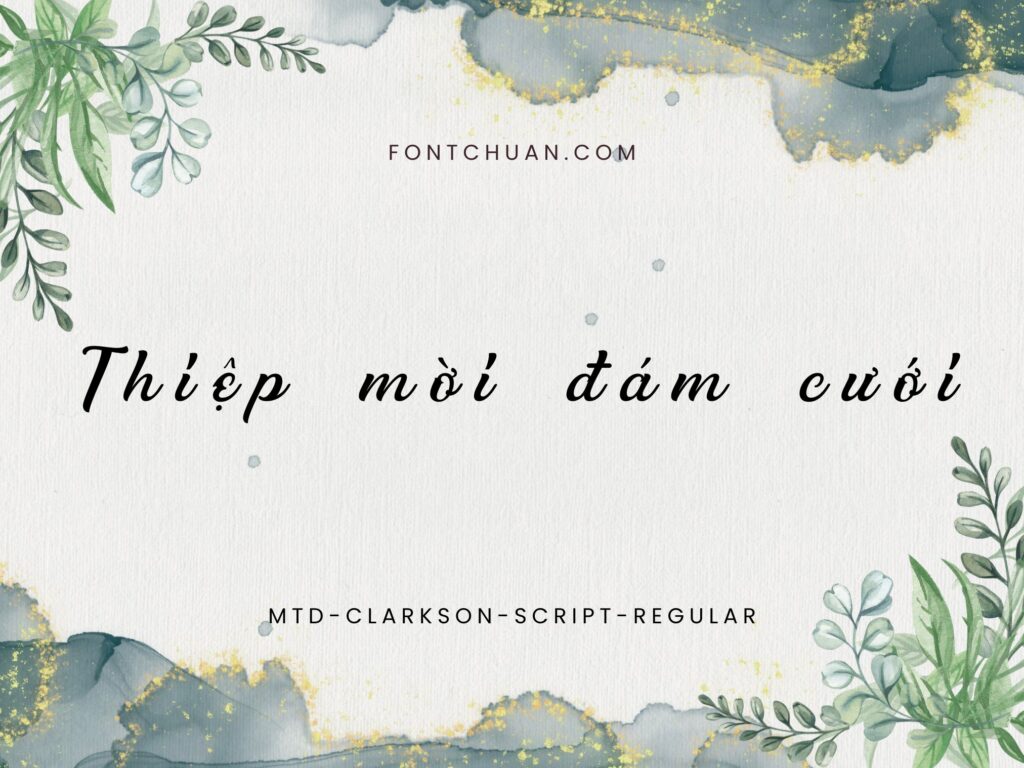
Font MTD Clarkson Script Việt Hóa
Tác giả Font: Adam Fathony
Font MTD Clarkson Script là một kiểu chữ viết tay thanh lịch, được thiết kế bởi Adam Fathony và đã được Việt hóa bởi Mộc Hạ. Font này hỗ trợ đầy đủ tiếng Việt cùng hơn 90 ngôn ngữ khác, mở rộng khả năng ứng dụng trong các thiết kế đa ngôn ngữ. Đây là một trong những phông chữ được cộng đồng thiết kế đánh giá cao và sử dụng trong nhiều dự án sáng tạo, đáp ứng nhu cầu đa dạng của người dùng.
MTD Clarkson Script nổi bật với các đường nét mềm mại và uyển chuyển, tạo cảm giác sang trọng và nghệ thuật. Font rất phù hợp cho các thiết kế logo, tiêu đề, bao bì sản phẩm, thiệp mời và các ấn phẩm đòi hỏi sự tinh tế và độc đáo. Các ngành nghề phù hợp bao gồm quảng cáo, giáo dục, công nghệ, thiệp cưới và ảnh cưới. Font này cũng lý tưởng cho các sự kiện như Tết, Giáng sinh, Valentine và các lễ hội khác.